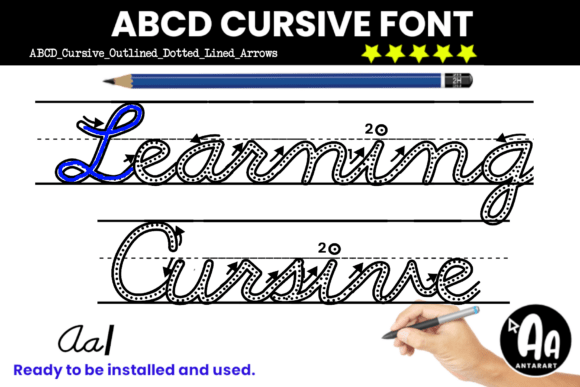
Abcd Cursive Outline Dotted Arrows Lined
適切なデザイン要素を見つけるのは難しい場合がありますが、Abcd Cursive Outline Dotted Arrows Linedは作品を即座に引き立てる優れたコレクションを提供します。
POD(オンデマンド印刷)製品、結婚式の招待状、またはソーシャルメディアのグラフィックを作成している場合でも、Abcd Cursive Outline Dotted Arrows Linedは理想的です。